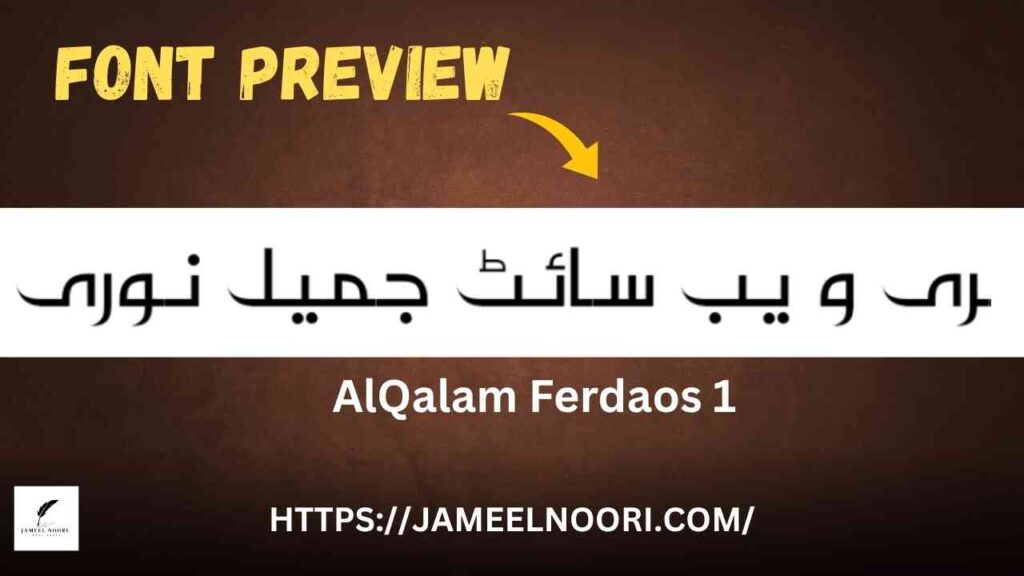
Introduction – Urdu Font AlQalam Ferdaos Kya Hai?
AlQalam Ferdaos  ek classy aur easy-to-read TrueType Urdu Nastaleeq font hai jo Urdu writing, designing, aur publishing projects ke liye specially design kiya gaya hai. Is font ne Urdu content creators ke darmiyan apni ek khaas pehchan bana li hai.
Key Features – AlQalam Ferdaos Font
• ✒️ Smooth Nastaleeq Style for elegant Urdu writing
• 🖋️ Perfect for designing Urdu poetry, quotes, and logos
Yeh Font Kahan Use Kiya Ja Sakta Hai?
AlQalam Ferdaos  Urdu font ka istamaal aap kai different projects mein kar sakte hain:
• 📚 Urdu books aur school content
• 🎨 Social media post designing (quotes, poetry)
• 📰 Urdu blog posts ya news article ke headings
• 📽️ Video editing aur Urdu captions banane ke liye
• 📄 Urdu PDFs aur flyers ke liye design
Conclusion – Apni Urdu Designs Ko Uplift Karein
Agar aap Urdu ke liye ek stylish aur highly rated Nastaleeq font ki talash mein hain to AlQalam Ferdaos  Urdu Font best choice hai. Is font se aap apne Urdu content ko professional aur readable bana sakte hain.